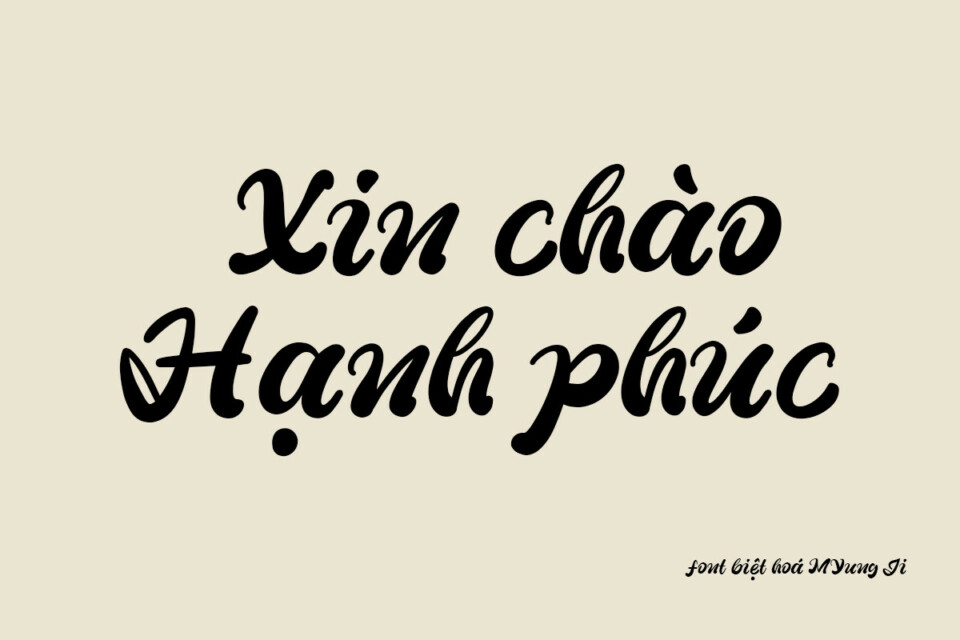
Giới thiệu về bộ Font việt hoá MJ Quickless
Trong thế giới đồ họa hiện đại, việc tìm kiếm một bộ Font Chữ vừa mang nét cá tính vừa hỗ trợ đầy đủ tiếng Việt là điều vô cùng quan trọng. Font việt hoá MJ Quickless nổi lên như một lựa chọn hàng đầu cho các nhà thiết kế yêu thích phong cách phóng khoáng và tốc độ. Với các đường nét thanh thoát nhưng không kém phần mạnh mẽ, bộ phông này giúp truyền tải thông điệp một cách ấn tượng. Đặc biệt, phiên bản việt hóa chuẩn giúp bạn không còn lo lắng về lỗi hiển thị dấu câu hay các ký tự đặc biệt trong tiếng Việt.
Đặc điểm nổi bật của MJ Quickless
Bộ font này sở hữu cấu trúc ký tự độc đáo, tạo cảm giác như được viết bằng tay một cách nhanh chóng nhưng vẫn giữ được sự tinh tế. Điều này giúp Font việt hoá MJ Quickless trở nên cực kỳ phù hợp cho các dự án thiết kế bìa sách, poster quảng cáo hoặc tiêu đề video. Đối với các bạn học sinh và giáo viên, đây cũng là công cụ hữu ích để làm mới các bài thuyết trình, giúp nội dung giáo dục trở nên sinh động và lôi cuốn hơn đối với người xem.
Ứng dụng thực tế và cách sử dụng hiệu quả
Bạn có thể sử dụng MJ Quickless trong nhiều ngữ cảnh khác nhau từ in ấn đến kỹ thuật số. Khi kết hợp với các tông màu sáng, font chữ sẽ tạo nên sự bùng nổ về thị giác. Ngược lại, khi dùng trên nền tối, nó mang lại cảm giác huyền bí và chuyên nghiệp. Để đạt hiệu quả tốt nhất, bạn nên sử dụng font này cho các phần tiêu đề lớn thay vì các đoạn văn bản dài để đảm bảo tính dễ đọc cho người dùng.
Kết luận về Font việt hoá MJ Quickless